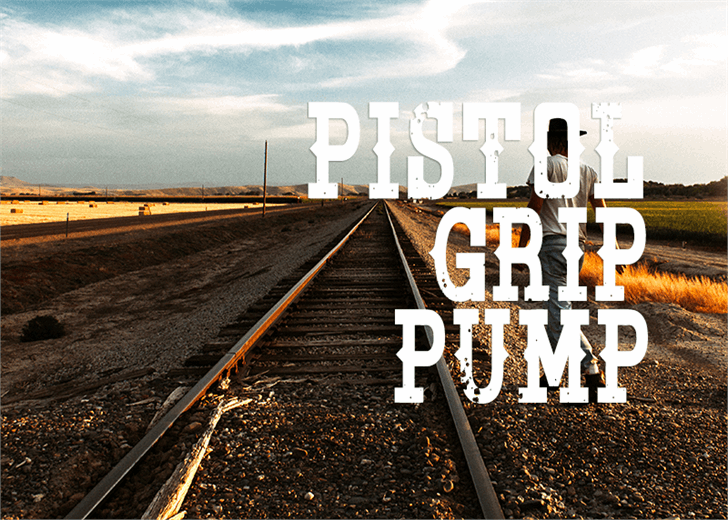
Pistol Grip Pump Font – Download Grátis
A Pistol Grip Pump Font é uma tipografia do gótico que oferece um visual agressivo e distante, perfeito para criar um tom único e interessante em design gráfico. Ideal para marcas criativos ou qualquer aplicação onde você deseja destacar-se com um estilo não convencional. O designer Hamilton trouxe a essência da tipografia do gótico ao seu ápice, adicionando um charme atento à segurança pública através de uma combinação única de linhas levemente inclinadas e curvas fortes. Esta fonte é ideal para trabalhos de design gráfico que precisam de um elemento diferenciador para destacar-se no mercado. O pistol grip pump é conhecido por sua força e simplicidade, e esta font gótica reflete exatamente isso, proporcionando um design sóbrio e poderoso. É perfeita para marcas criativos ou qualquer aplicação onde você deseja destacar-se com um estilo não convencional. A Pistol Grip Pump Font é uma escolha ótima para designers que valorizam estilos únicos e querem criar designs altamente diferenciados. Seja em materiais de publicidade, arte digital ou design gráfico, a Pistol Grip Pump se destaca por sua forte presença visual e linguagem clara. Estamos ansiosos para ver como você usará esta fonte poderosa. Experimente uma experiência com essa font do gótico que oferece um olhar intrigante e diferenciado em suas criações gráficas.